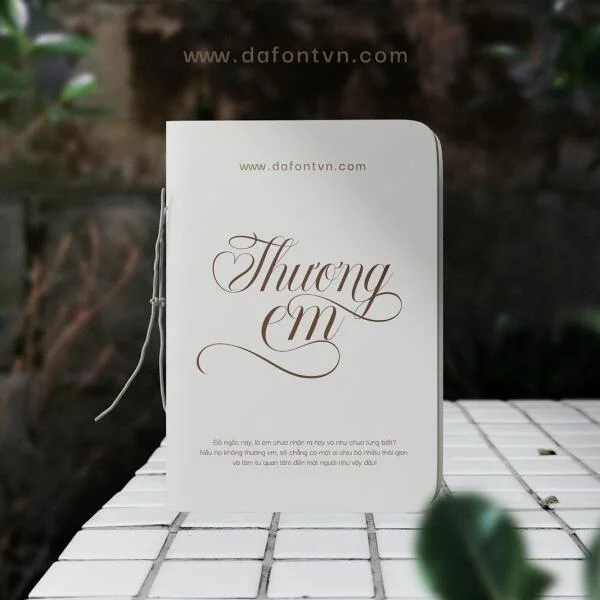
Tổng quan về Font Mongek
Mongek font được thiết kế với phong cách hiện đại, đơn giản và năng động. Kiểu serif được sử dụng bởi phông chữ Mongek là phông chữ kiểu 2022, có một sự thay thế swash độc đáo, có nhiều lựa chọn chữ ghép. Thêm vao Đoa.
Mongek rất dễ áp dụng cho bất kỳ thiết kế nào có thể kể đến như xây dựng thương hiệu, tạp chí, bìa truyện, thiệp mời, typography, quotes, đặc biệt là những kiểu chữ có thiết kế thanh lịch và mượt mà.
Font việt hóa Mongek
Mongek Typeface
Mẫu 1
Font Mongek việt hóa siêu đẹp
Mẫu 2
Font làm typography, quotes
Mẫu 3
Font việt hóa chất lượng cao
Mẫu 4
Chi tiết các ký tự font việt hóa Mongek
Font việt hóa Mongek gồm 3 kiểu: Thin - Regular - Bold, được mã hóa Unicode (PUA) để sử dụng cho bất kỳ chương trình thiết kế hoặc phi thiết kế vì mọi thứ đều thay đổi và glyph đều được hỗ trợ.
Mongek Typeface - All Character
Chi tiết ký tự